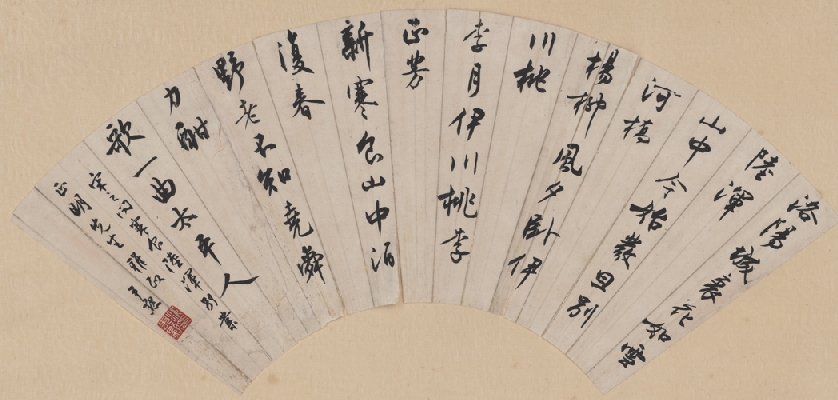
沈尹默
沈尹默简介
沈尹默,原名君默,号秋明。著名学者、诗人、书法家、教育家。 1883年6月11日出生于陕西汉阴县城。1905年留学日本,1913年起历任北京大学国文系教授兼国文门研究所主任、河北省教育厅长、北平大学校长等职。新中国成立后,任中央文史馆副馆长、上海书法篆刻委员会主任、上海市文联副主席等职。“五四”运动时,为《新青年》编辑之一,首倡新诗,旧体诗词功力颇深。书法精于用笔,于笔法、笔势多所阐发,被海内外公认为一代书宗和现代中国书法第一人。著有《历代名家书法经验谈辑要释义》、《二王法书管窥》等。
沈尹默真迹高清原图大图